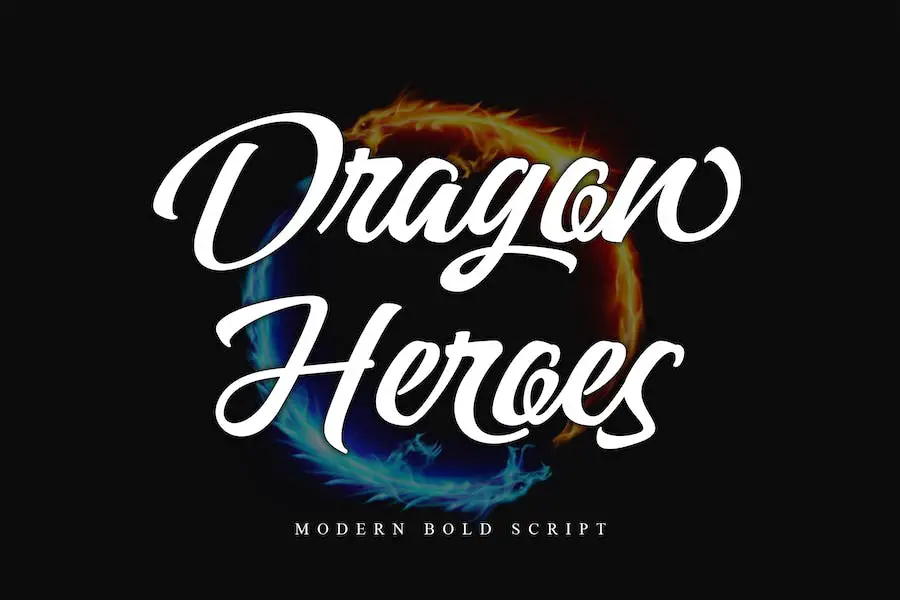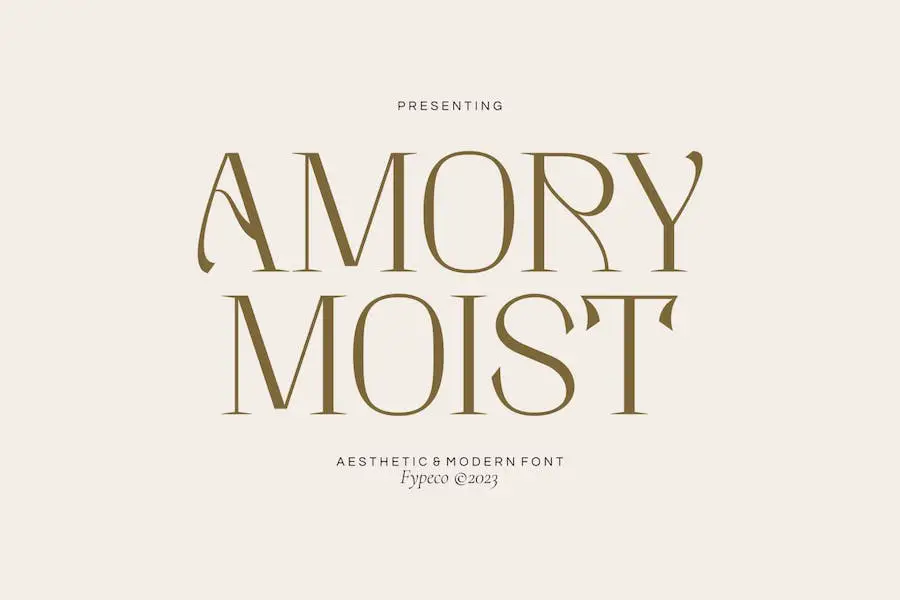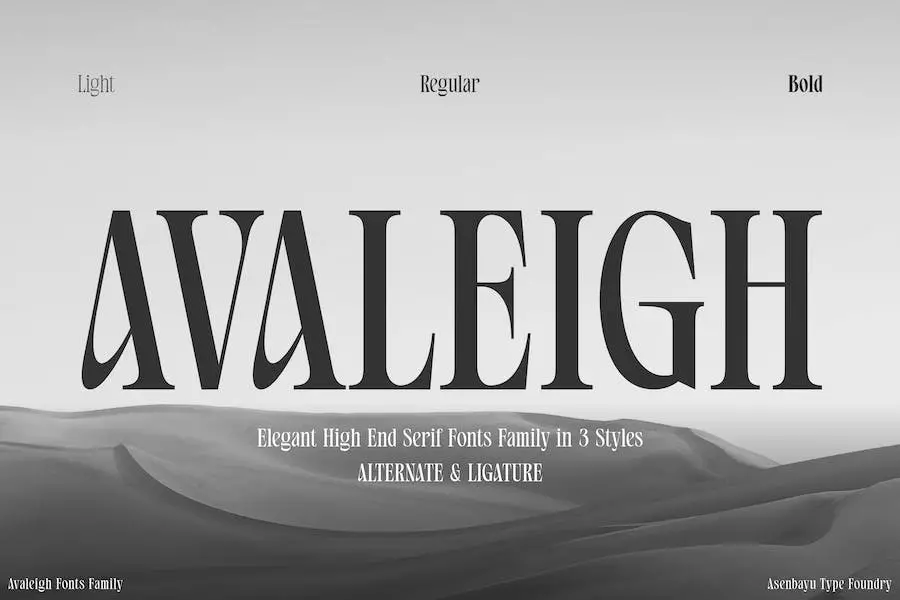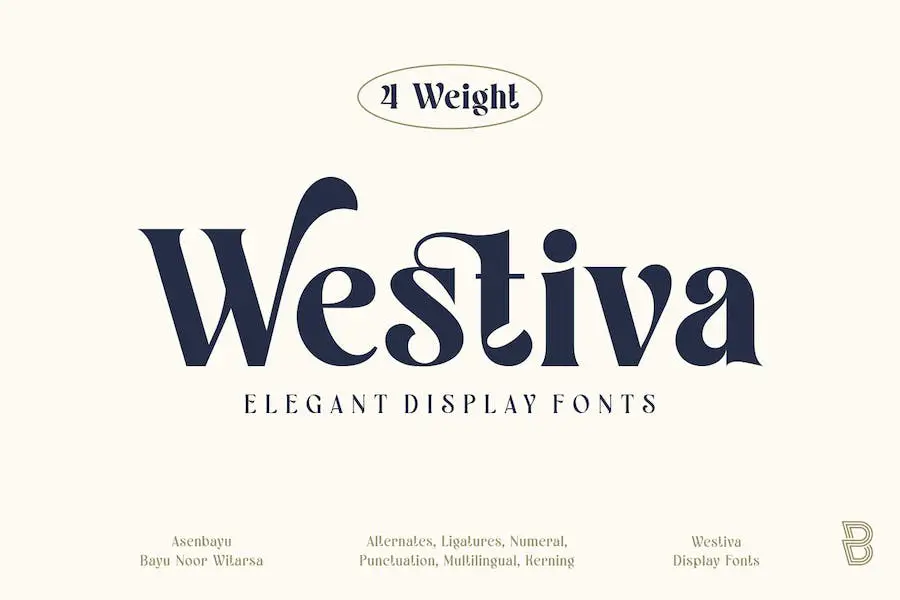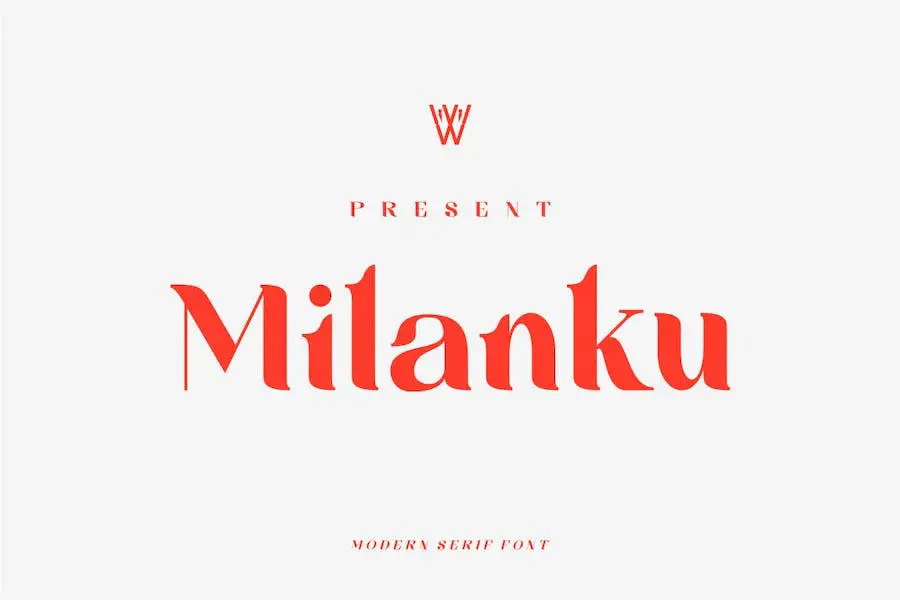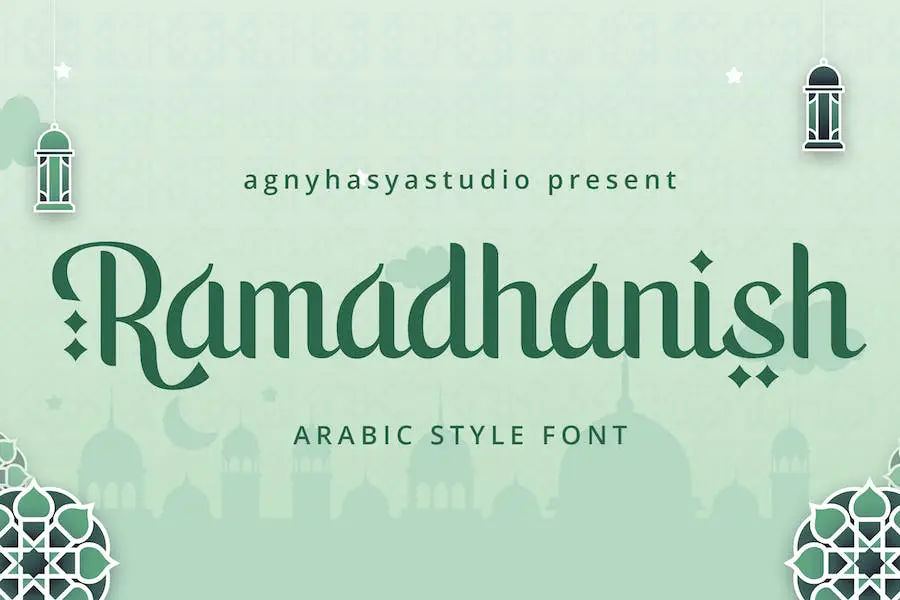
15 Font Ibrani Terbaik 2023 (Gratis & Premium)
Diterbitkan: 2023-09-25Apakah Anda seorang desainer grafis, pengembang web, atau profesional kreatif yang ingin menyempurnakan proyek desain Anda dengan sumber daya maket berkualitas tinggi?
Jika iya, Anda datang ke tempat yang tepat! Dalam postingan blog ini, kita akan mendalami dunia font Ibrani dan mengeksplorasi bagaimana font tersebut dapat menambahkan sentuhan unik pada desain Anda.
Sekarang, Anda mungkin bertanya-tanya, mengapa menggunakan huruf Ibrani? Nah, dengan semakin populernya desain global dan meningkatnya permintaan akan situs web dan branding multibahasa, memiliki koleksi font Ibrani di gudang desain Anda bisa menjadi sangat berharga.
Font memainkan peran penting dalam mengekspresikan kepribadian dan corak desain, dan menggabungkan font Ibrani dapat menghadirkan kedalaman dan kekayaan budaya pada proyek Anda.
Sebelum kita masuk ke seluk beluk font Ibrani, mari luangkan waktu sejenak untuk menghargai pentingnya tipografi dalam desain.font
Tahukah Anda bahwa 95% dari semua proyek desain melibatkan tipografi? Tipografi bukan hanya tentang memilih font yang tepat tetapi juga tentang memanfaatkannya secara efektif untuk menyampaikan pesan Anda dan menciptakan komposisi yang menarik secara visual.
Memilih font Ibrani yang sempurna dapat menjadi penentu dalam membuat desain Anda menonjol dan sesuai dengan target audiens Anda.
Dalam artikel ini, kami akan menjelajahi font Ibrani terbaik untuk berbagai proyek desain, berbagi tips tentang cara menggabungkannya dengan lancar, dan memberi Anda sumber daya berharga untuk mengakses font Ibrani berkualitas tinggi.
Jadi, bersiaplah dan bersiaplah untuk terjun ke dunia tipografi Ibrani. Mari buat desain Anda bersinar dengan keindahan font Ibrani!
Font Ibrani Premium Terbaik
Apakah Anda seorang desainer grafis yang ingin menambahkan sentuhan elegan dan keaslian pada desain Anda? Tidak perlu mencari lagi!
Koleksi Font Ibrani Premium Terbaik kami pasti akan mengesankan dan meningkatkan proyek Anda ke tingkat yang benar-benar baru. Jangan lewatkan font menakjubkan ini – lihat sekarang dan biarkan kreativitas Anda melambung!
Tcho adalah jenis huruf yang sangat serbaguna yang menawarkan dukungan untuk berbagai bahasa dan beragam fitur Opentype. Dengan koleksi karakter alternatif, bentuk angka berbeda, dan bentuk swash, font ini memungkinkan kemungkinan kreatif tanpa batas.
Baik Anda sedang mengerjakan proyek branding internasional yang memerlukan gaya visual yang konsisten di berbagai sistem penulisan atau sekadar ingin menambahkan sentuhan unik pada desain Anda, Tcho siap membantu Anda.
Selain mencakup skrip Latin, Sirilik, Yunani, Ibrani, Arab, dan Thailand, font Ibrani Google ini juga menyertakan bobot miring yang indah yang menambah kesan kaligrafi pada desain Anda. Tcho benar-benar harus dimiliki oleh setiap desainer grafis yang ingin meningkatkan proyek mereka.
Natan
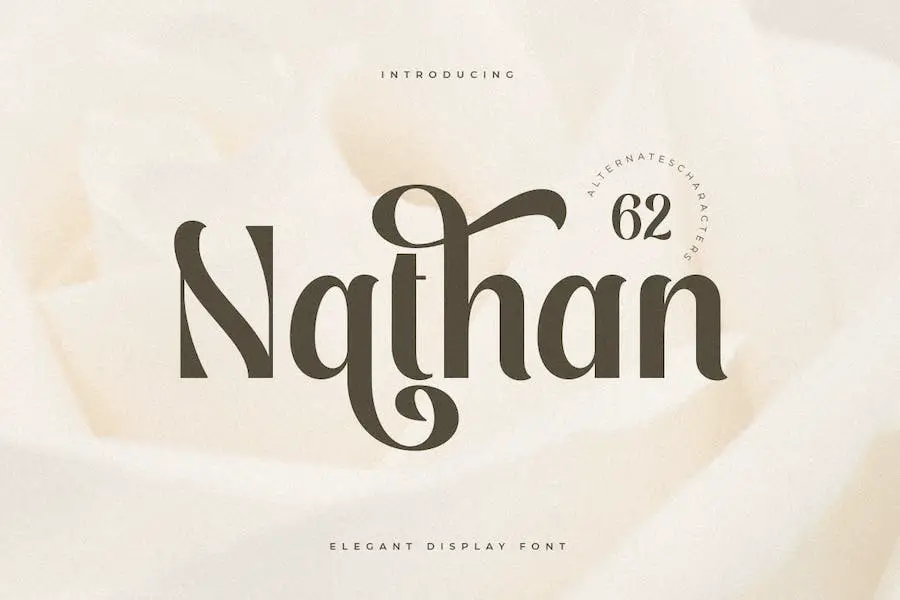
Nathan adalah font Elegant Display Serif yang dirancang khusus bagi mereka yang ingin menambahkan sentuhan elegan pada proyek branding mereka. Bentuknya yang unik menambah nilai brand Anda sehingga terlihat lebih gaya dan modern.
Nathan adalah solusi sempurna bagi desainer dan pemilik produk yang ingin meningkatkan desain mereka ke level berikutnya.
Dengan 4 format yang tersedia (.otf, .ttf, .woff, .woff2), Nathan siap memenuhi kebutuhan kreatif Anda. Muncul dengan karakter huruf kecil dan besar, memungkinkan Anda membuat variasi tak terbatas untuk proyek Anda. Baik Anda mendesain poster, logo, atau situs web, Nathan siap membantu Anda.
Jadi, jika Anda seorang desainer grafis yang mencari font yang akan membawa desain Anda ke tingkat yang lebih tinggi, Nathan adalah pilihan yang tepat.
Ini adalah alat sempurna untuk menambahkan sentuhan keanggunan dan modernitas yang akan membuat proyek Anda bersinar. Jangan lewatkan kesempatan untuk meningkatkan karya kreatif Anda dengan font Adobe Ibrani yang menakjubkan ini. Dapatkan Nathan hari ini dan bawa desain Anda ke level berikutnya.
Pegunungan
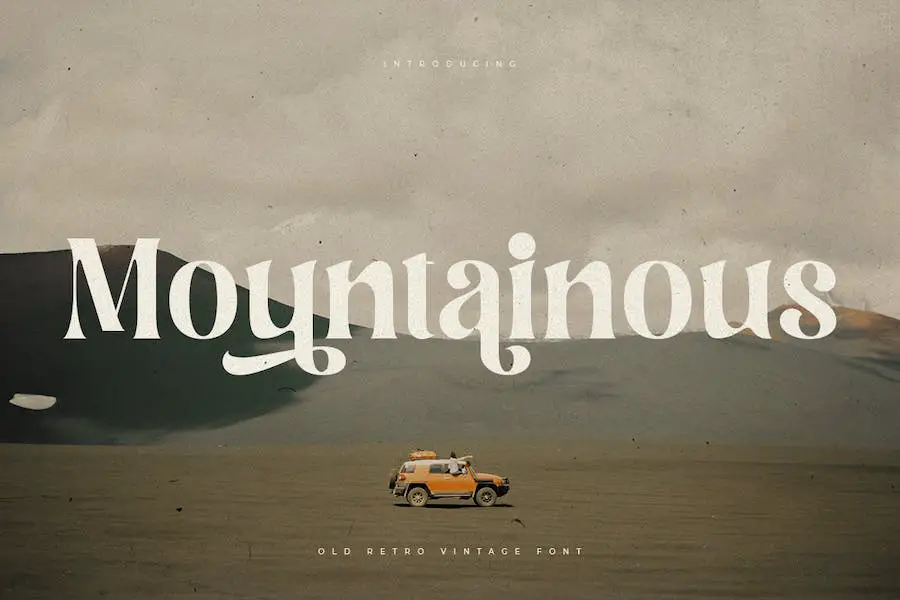
Montainous adalah font Old Retro Vintage yang sempurna untuk menambahkan tampilan unik dan vintage pada proyek desain Anda.
Dengan karakter huruf kecil dan besar, ia menawarkan fleksibilitas luar biasa untuk judul dan kebutuhan branding. Muncul dengan 4 format file berbeda (.otf, .ttf, .woff, dan .woff2) agar mudah digunakan di PC dan Mac.
Font ini adalah solusi bagus bagi desainer dan pemilik produk yang ingin membuat desain mereka menonjol dengan sentuhan vintage. Alternatif ekstra dalam gaya unik menambah nilai lebih pada merek Anda.
Baik Anda sedang mengerjakan proyek retro vintage atau membutuhkan font yang menghadirkan sentuhan nostalgia, Montainous adalah pilihan yang tepat. Mudah digunakan dan menawarkan berbagai kemungkinan untuk menyempurnakan desain Anda.
Jadi, jika Anda mencari font yang akan membawa proyek Anda ke level berikutnya dan memberikan kesan unik dan vintage, font Ibrani untuk Word adalah font yang tepat untuk Anda. Cobalah dan lihat perbedaannya pada desain Anda.